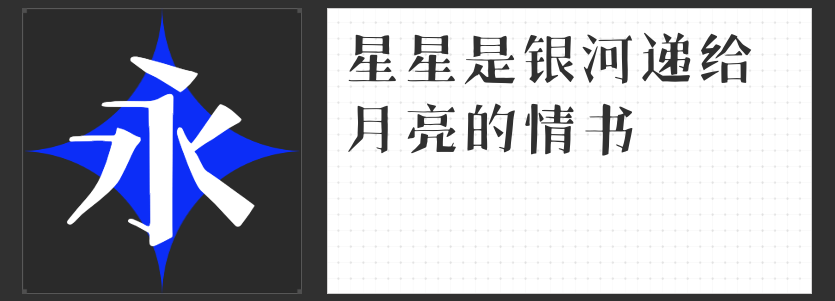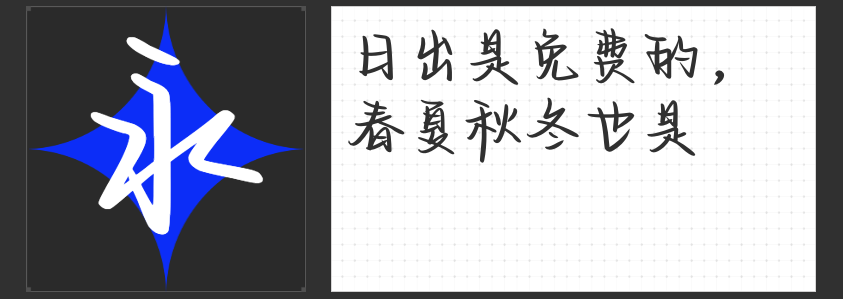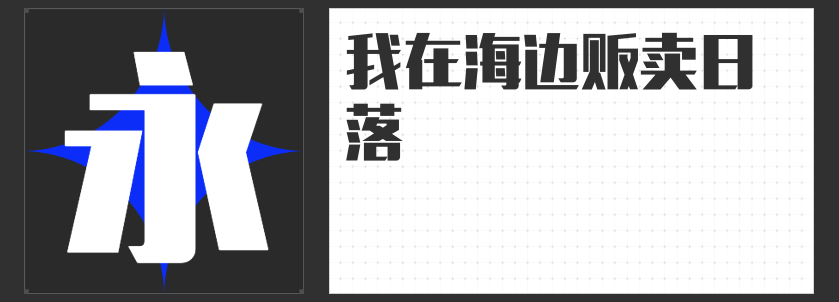
婚庆字体精选:让爱意在字里行间绽放
在筹备婚礼的每一个细节中,字体的选择都承载着新人对爱情的美好寄托与对未来的无限憧憬。今天,我们精心挑选了四款特别适合用于婚庆用品的字体,它们不仅各具特色,更能完美融入不同婚礼主题,让每一份邀请、每一份礼物都充满爱的温度。
1.造字侠热辣隶简
这款字体以其独特的隶书韵味,为传统中式婚礼增添了几分庄重与喜庆。无论是婚礼红包上的烫金大字,还是请柬上的温馨寄语,造字侠热辣隶简都能完美呈现那份古典美与仪式感,让宾客在第一时间感受到婚礼的庄重与温馨。
当婚礼的回忆录缓缓播放,这款手写风格的字体仿佛带着我们穿越回青涩的初恋时光。它的每一笔一划都充满了故事感,让人在回忆中感受到爱情的甜蜜与成长的不易。用也字工厂电影旁白体来制作婚礼视频的字幕,定能触动每一位观众的心弦。
3.高手庆科手绘宋
在婚礼现场,一款既具宋体端庄又不失手写韵味的字体显得尤为重要。高手庆科手绘宋正是这样一款字体,它巧妙地将宋体的严谨与手绘的随性相结合,无论是用于易拉宝上的婚礼介绍,还是酒店门口的欢迎词,都能让宾客感受到一种亲切与温馨的氛围。
4.励字造灿烂黑
时尚与浪漫并存,这款黑体字体以其独特的魅力成为了喜糖礼盒、回礼包装上的不二之选。它的线条简洁流畅,色彩鲜明夺目,既展现了新人的时尚品味,又寓意着他们未来生活的灿烂与美好。
选择一款合适的婚庆的字体,不仅能让婚礼用品更加美观大方,更能传递出新人对爱情的美好愿景与对未来的无限憧憬。希望这四款字体能为你的婚礼增添一抹独特的色彩,让爱意在字里行间绽放。